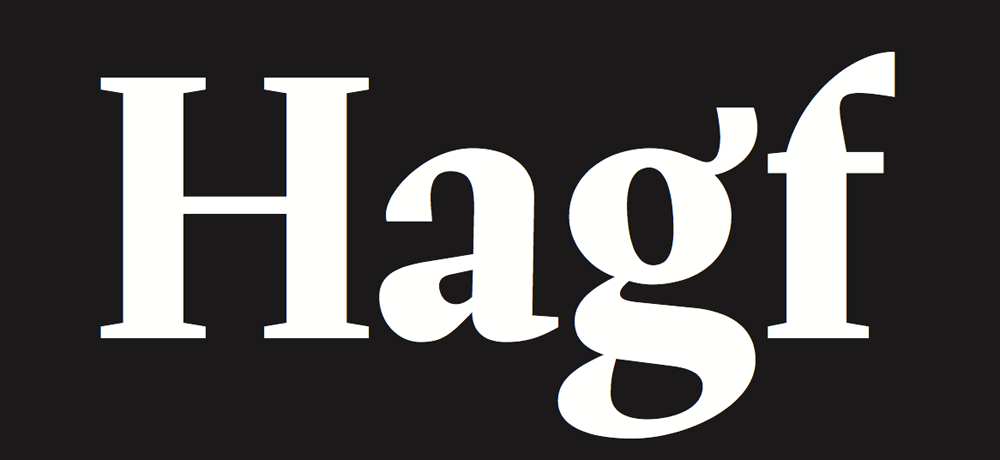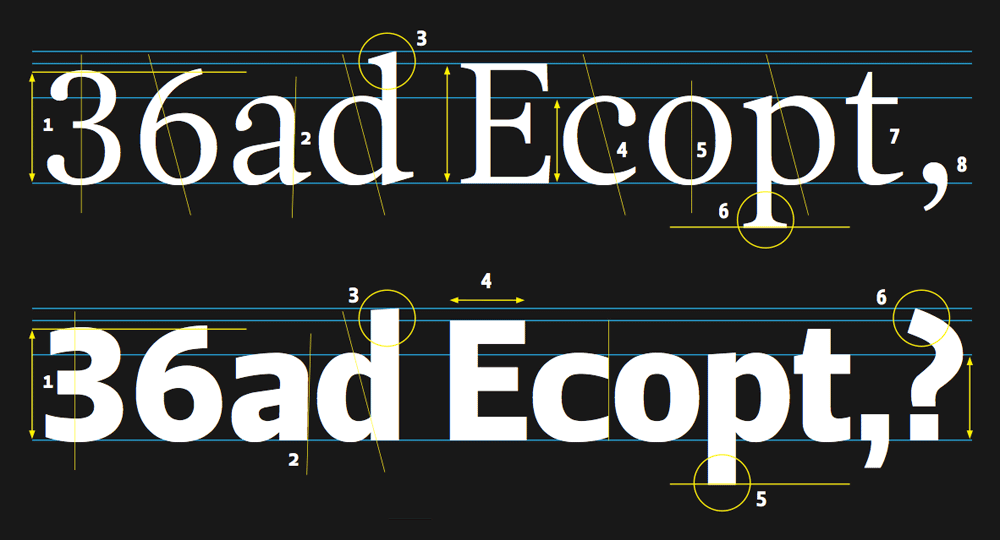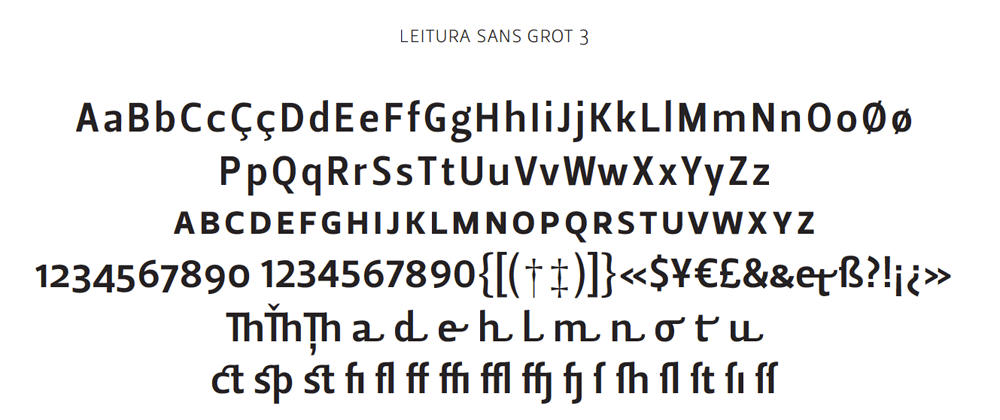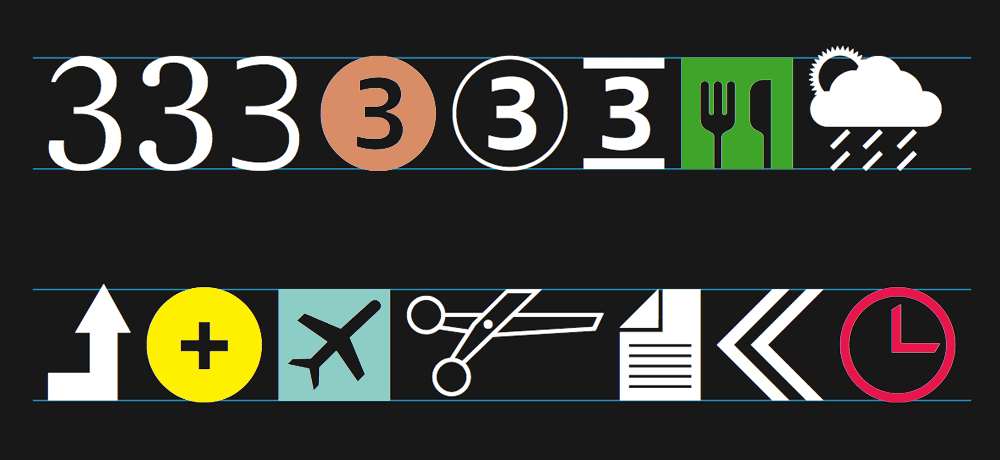
Wer seine Sachen gerne selbst repariert, schätzt gutes Werkzeug. Sogenannte Universalschrauber oder -schlüssel sind mit Vorsicht zu genießen. Meistens können sie nichts richtig. Einmal zu fest angezogen, geben sie rasch ihren (patentierten) Geist auf. Nicht umsonst bedienen sich Profis fein aufeinander abgestimmter Schlüsselsätze oder Schraubendreher-Sets. Die sind zwar umfangreich und wiegen ihren Teil, dafür gibt es für jede Schraube das genau passende Tool.
Bei der Wahl einer Schrift für bestimmte Aufgaben gelten ähnliche Gesetze. Eine Universalschrift leistet in den Händen von Laien gute Dienste, sie ist leicht zu bedienen, schnelle Erfolgserlebnisse sind garantiert. Doch auch für Typografen gibt es Spezialwerkzeuge, die nicht jeder bedienen sollte. In den Händen von Profis bewirken sie wahre Wunder. Die Leitura-Schriftsippe von Dino dos Santos ist eine solcher Schrift-Werkzeugkasten. Er besteht aus den »Schlüsselsätzen« Leitura (Serif) Complete, Leitura News Complete, Leitung Sans Complete, Leitura Headline Complete, Leitura Display Complete, Leitura Symbols Complete. Der Name »News« für die kräftigere Serifen-Version verrät: Leitura wurde für den Einsatz in Zeitungen, Zeitschriften und den Werksatz entwickelt, der anspruchsvollsten typografischen Baustelle.
Der Entwerfer der Leitura, Dino dos Santos, beschreibt seinen Designansatz so: »Ich wollte eine Handvoll neutraler und belastbarer Schriften entwickeln, mit möglichst wenig Schnickschnack der vom Lesen ablenkt.« So entstand eine Sippe aus 6 Teilfamilien, vorzüglich ausgebaut, einschließlich eines umfassenden Symbol-Zeichensatezes.
Sicherlich ist Leitura nicht die erste gut ausgebaute Schriftsippe für den Editorial-Design-Bereich, man denke nur an die neuere Greta von Peter Bilak (Typotheque). Aber keine bietet einen größeren stilistischen Kontrast, im Rahmen der engen Verwandtschaft der einzelnen Subfamilien. Während bei vielen Serif-Sans-Sippen ziemlich deutlich erkennbar der eine Stil aus dem anderen hergeleitet wurde, scheinen die Leitura-Klassen aus sich heraus entstanden zu sein … ohne »angeklebte« oder »abgeschnittene« Serifen. Es grenzt an Zauberei wie Dos Santos mit klassischen Stilen (Transitional, Didone, Egyptienne) spielt, wie er Schwungbuchstaben und florale Elemente hinzufügt, und trotzdem harmoniert alles miteinander.
…also die Dingbats harmonieren nicht. Völlig verschiedene Stile.
Die Leitura ist seit Jahren meine Hausschrift. Sie hat so ihre Eigenarten – positiv wie negativ.